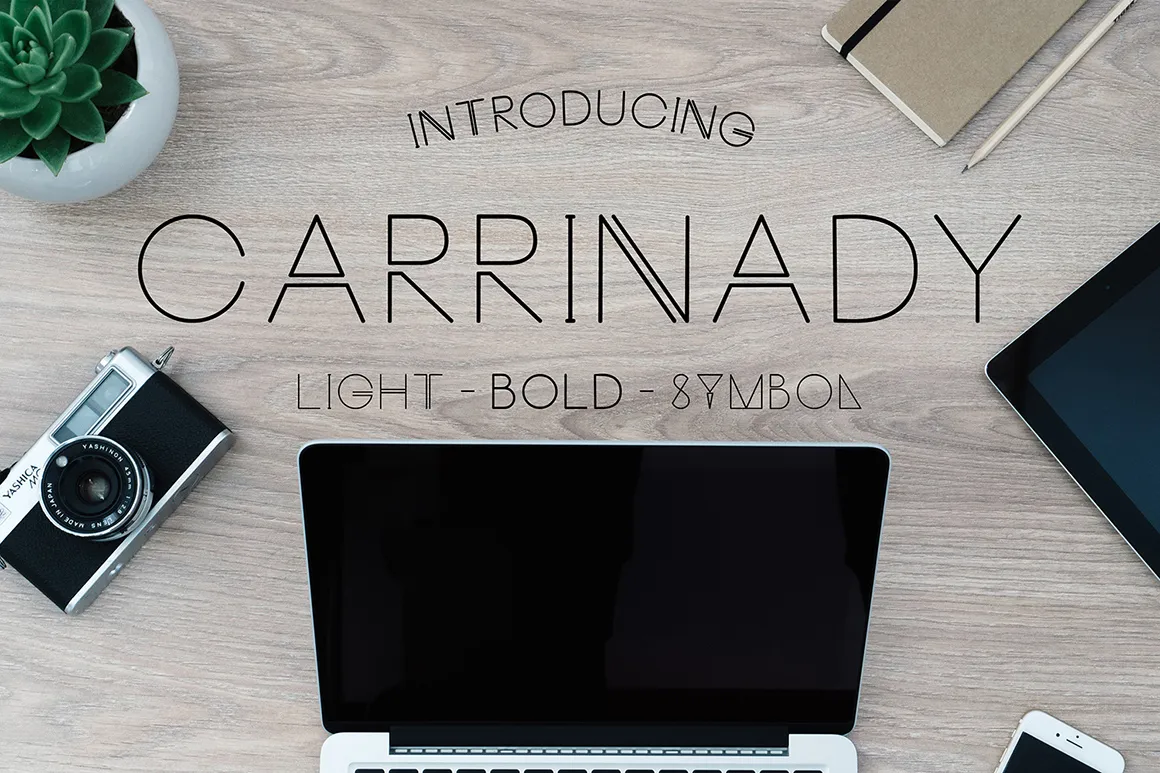
A Carrinady Typeface é uma fonte tipo Display projetada para oferecer um charme único e um toque distintivo a qualquer projeto visual. Com linhas fortes e elegantes, essa fonte combina elementos do moderno com nuances de antiguidade, criando um equilíbrio perfeito entre força e suavidade. Está disponível em versões gratuitas e completas, o que permite aos designers explorar todas as possibilidades dessa beleza visual. A madeDuk é um designer talentoso responsável pela criação desta fonte, garantindo uma qualidade excepcional em cada caractere. Se você está procurando por uma fonte capaz de destacar seu trabalho e torná-lo ainda mais chamativo, a Carrinady Typeface poderia ser exatamente o que você precisa. Para usufruir da versão completa desta fonte, basta clicar no link abaixo, disponível em nossa página. Procure por detalhes únicos e elegantes no design de cada caractere, seja para uso personalizado ou impressões digitais que certamente vão chamá-los a atenção.